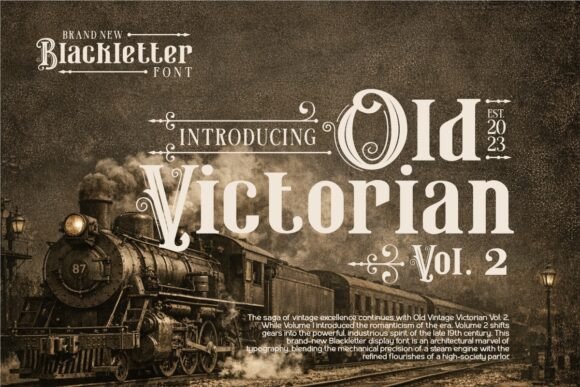
Old Victorian Vol 2
Trouver les bons éléments de conception peut être un défi, mais Old Victorian Vol 2 propose une collection exceptionnelle qui rehausse instantanément votre travail.